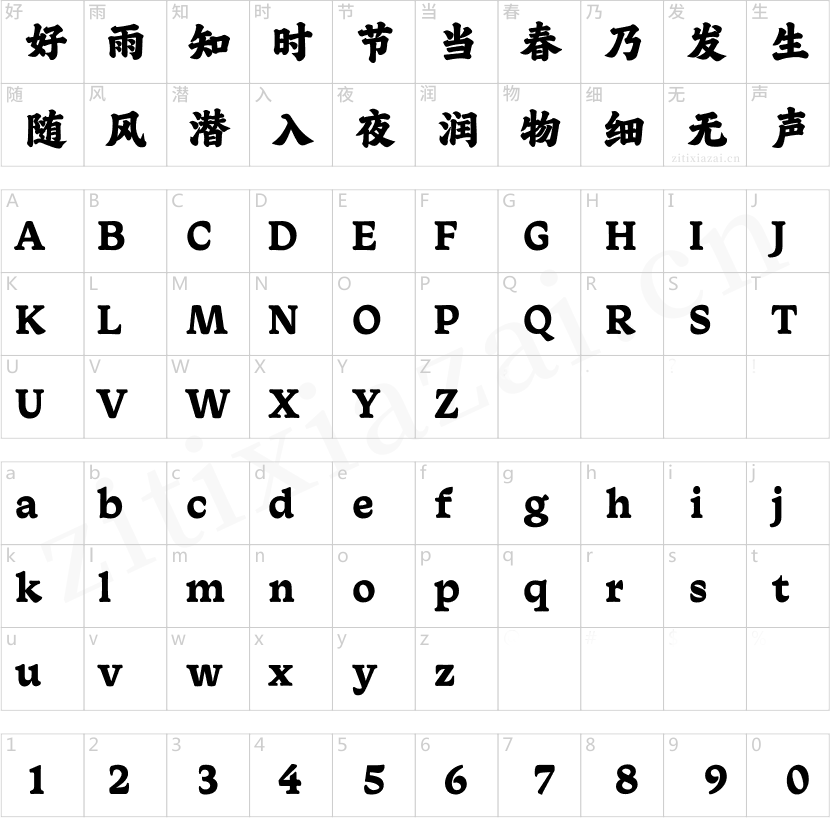
Aa福禄榜书
Aa福禄榜书,这款字体结构工整、笔画清晰,兼顾美观与易读性,适用于标题、正文、海报、包装、LOGO 等多种场景。字形优雅稳定,风格百搭耐看,适配日常排版与创意设计,让文字呈现更舒适、更具质感。Aa福禄榜书一笔一画,皆是细节,以均衡的比例、流畅的线条打造舒适视觉体验,字形端正大气,风格简约现代。无论是商业设计、品牌宣传还是日常排版,都能轻松驾驭,让文字更有格调与力量。Aa福禄榜书字体下载。
Aa福禄榜书字体
Aa福禄榜书是一款非常具有艺术性的字体,它的设计灵感来源于对古典艺术的研究,同时又融入了现代字体设计的元素。字形优美,笔画粗细变化自然,给人以大气、典雅的感觉。Aa福禄榜书是一款既传统又现代的字体,它的设计充满艺术感,美观大方,实用性也非常强。无论是对于设计师还是对于普通读者来说,都是一种非常不错的字体选择。Aa福禄榜书适合用于具有艺术感的场合,比如海报、宣传单张、书籍封面等。由于其字形流畅且具有动态感,也适合用于大量的文本排版,如报纸、杂志等。